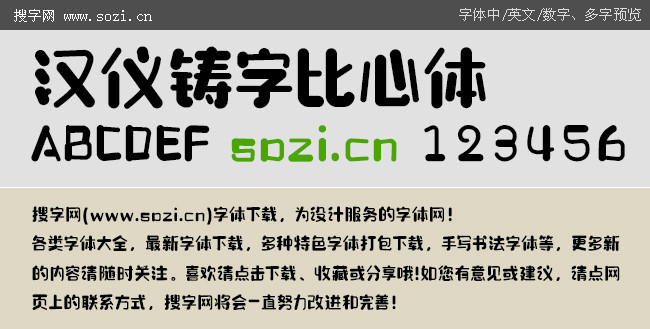
漢儀鑄字比心體
搜字網(wǎng)給大家提供一款漢儀鑄字比心體中文字體下載,漢儀鑄字比心體字體筆觸粗細(xì)適中,書寫端正,具有很好的視覺感,適合應(yīng)用于藝術(shù)設(shè)計(jì)、平面宣傳設(shè)計(jì)、網(wǎng)頁設(shè)計(jì)等眾多設(shè)計(jì)場(chǎng)合。(本字體為個(gè)人非商用版,如需要商用請(qǐng)聯(lián)系漢儀公司購買版權(quán))